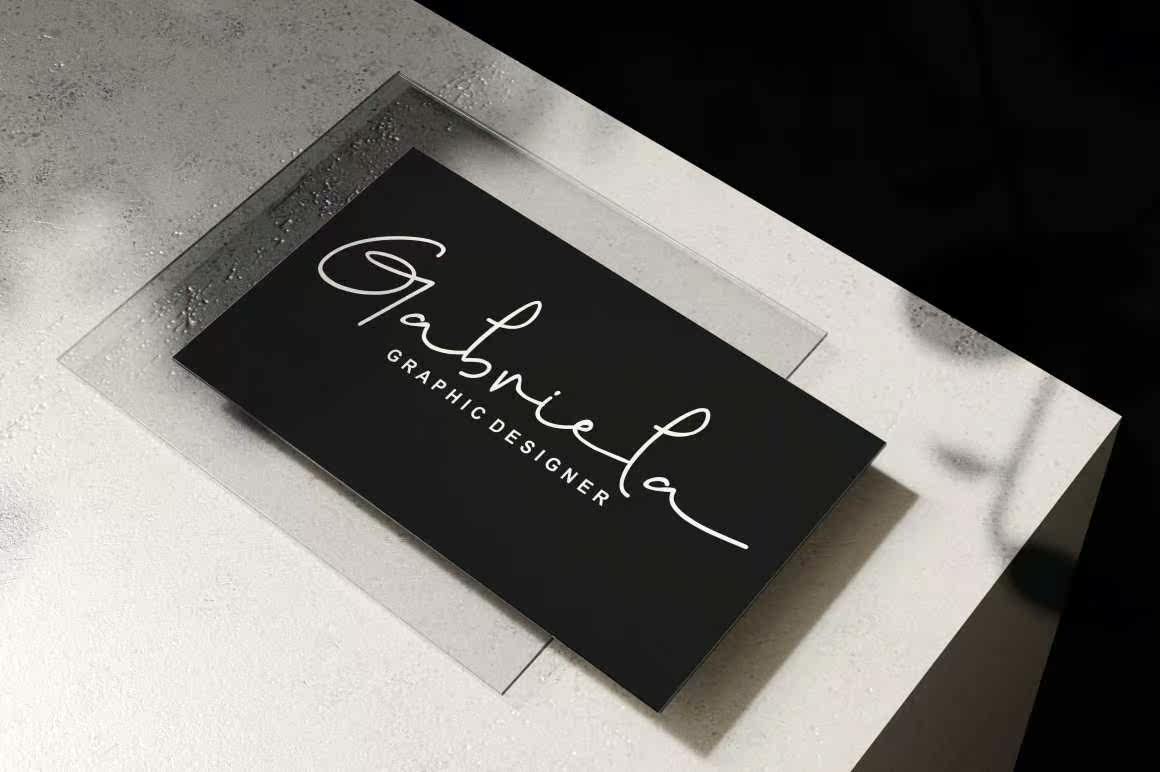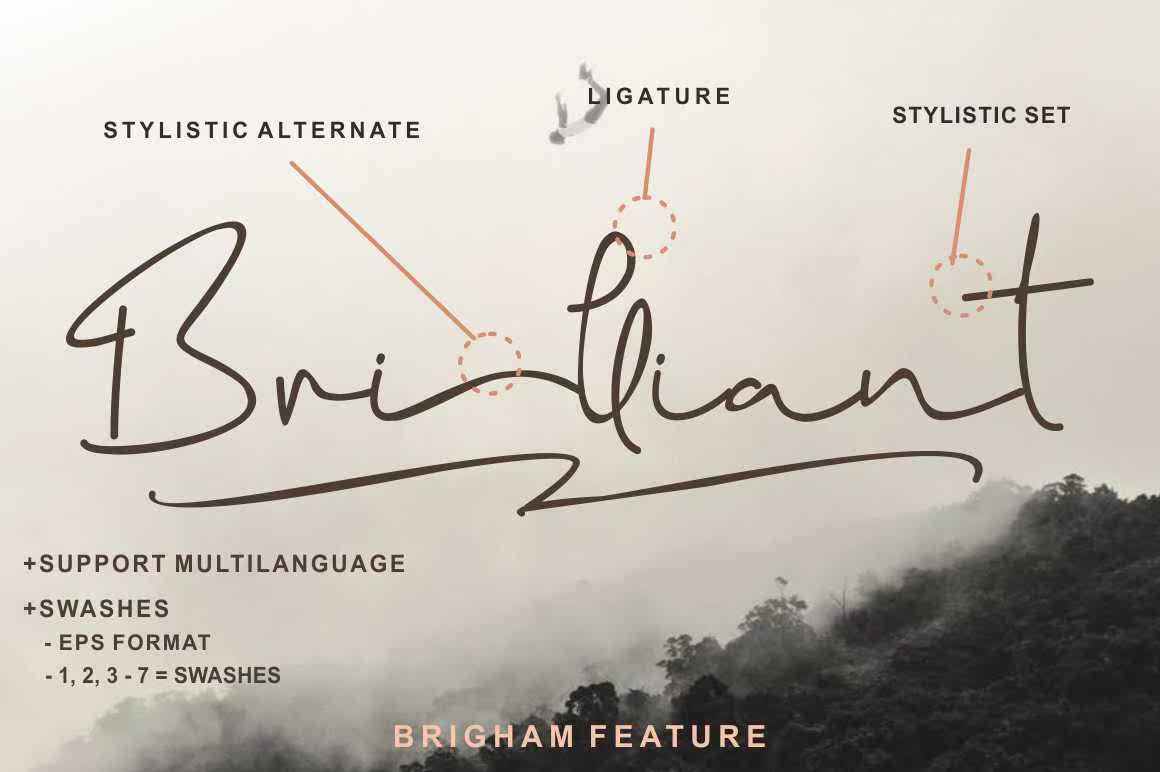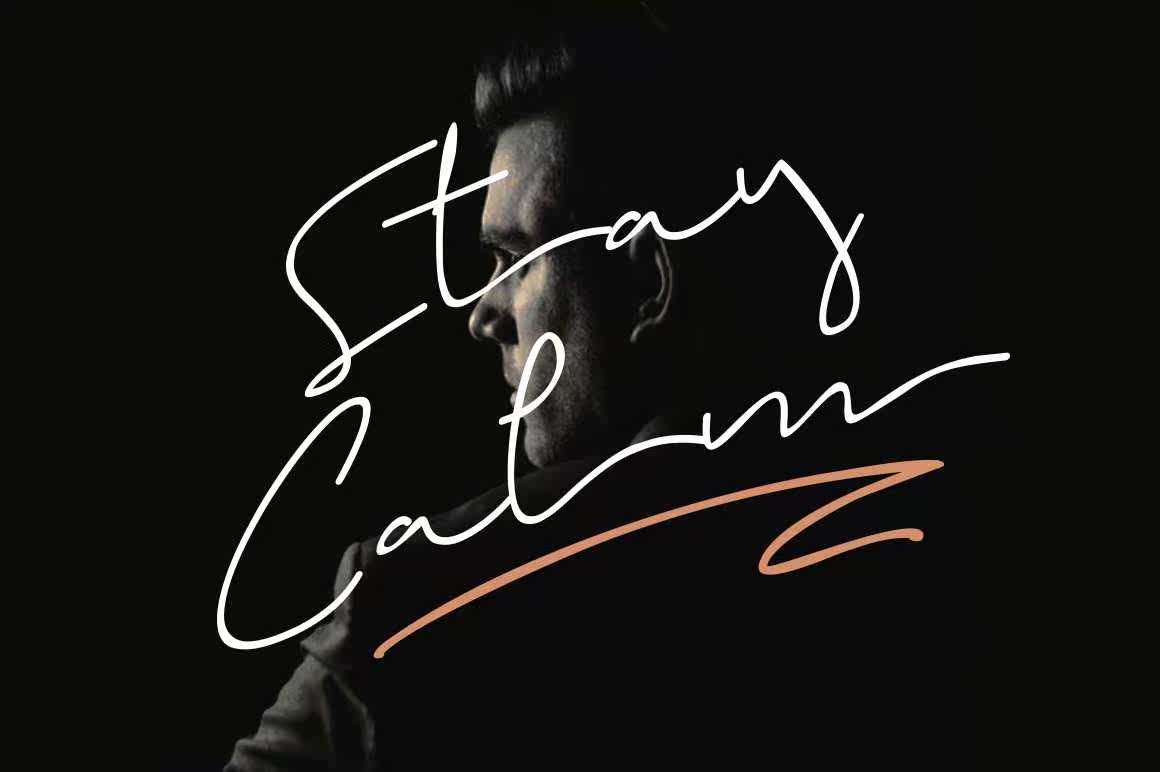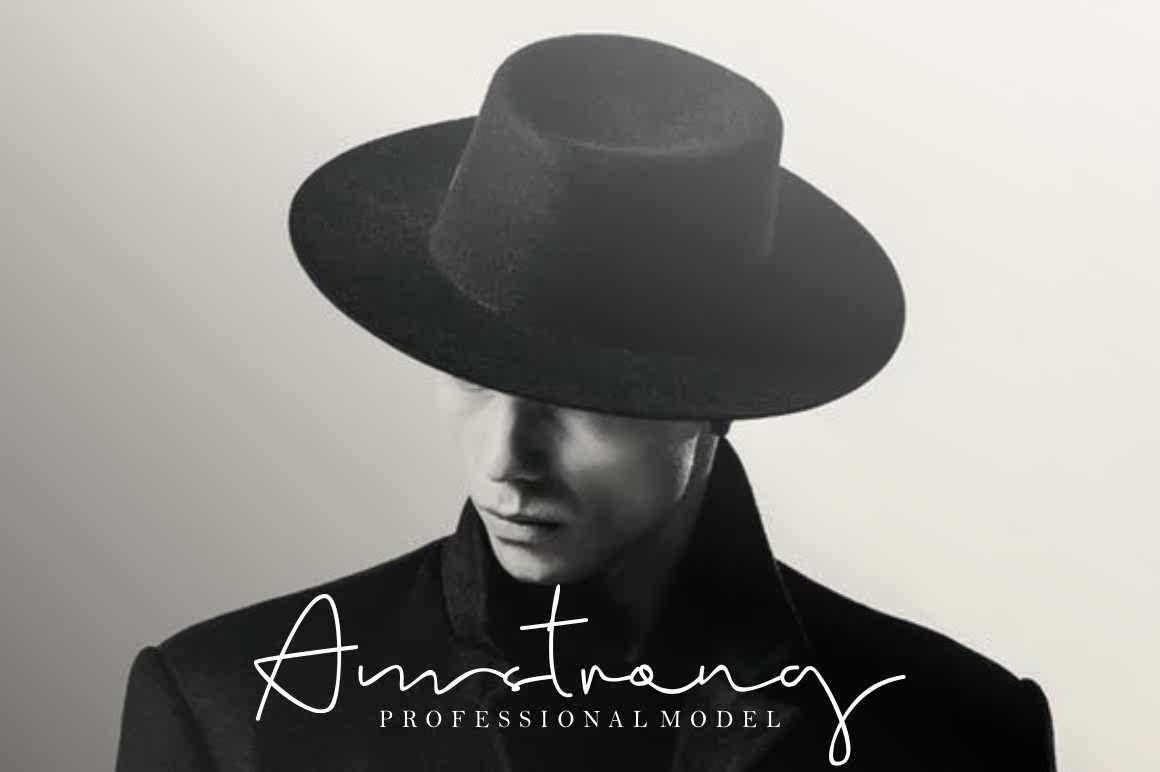
Brigham签名是具有自然流动和风格的手写张力签名。Fontsareluxurious和Legant具有自然和刮痕。此签名适用于个人品牌,如面试、名片、产品标识集C。Brigham签名完美地描述了品牌项目、标识、婚礼设计、社交媒体、广告、产品包装、,产品设计、标签、摄影、水印、邀请函、文具和许多需要手写签名的项目。Brigham签名是具有自然流和风格的手写签名。Fontsareluxurious和Legant具有自然流和划痕。此签名适用于个人品牌,如采访、名片、,产品标识集c.BrighamSignatures是品牌项目、标识、婚礼设计、社交媒体、广告、产品包装、产品设计、标签、摄影、水印、邀请函、文具和需要手写签名的任何项目的完美描述。